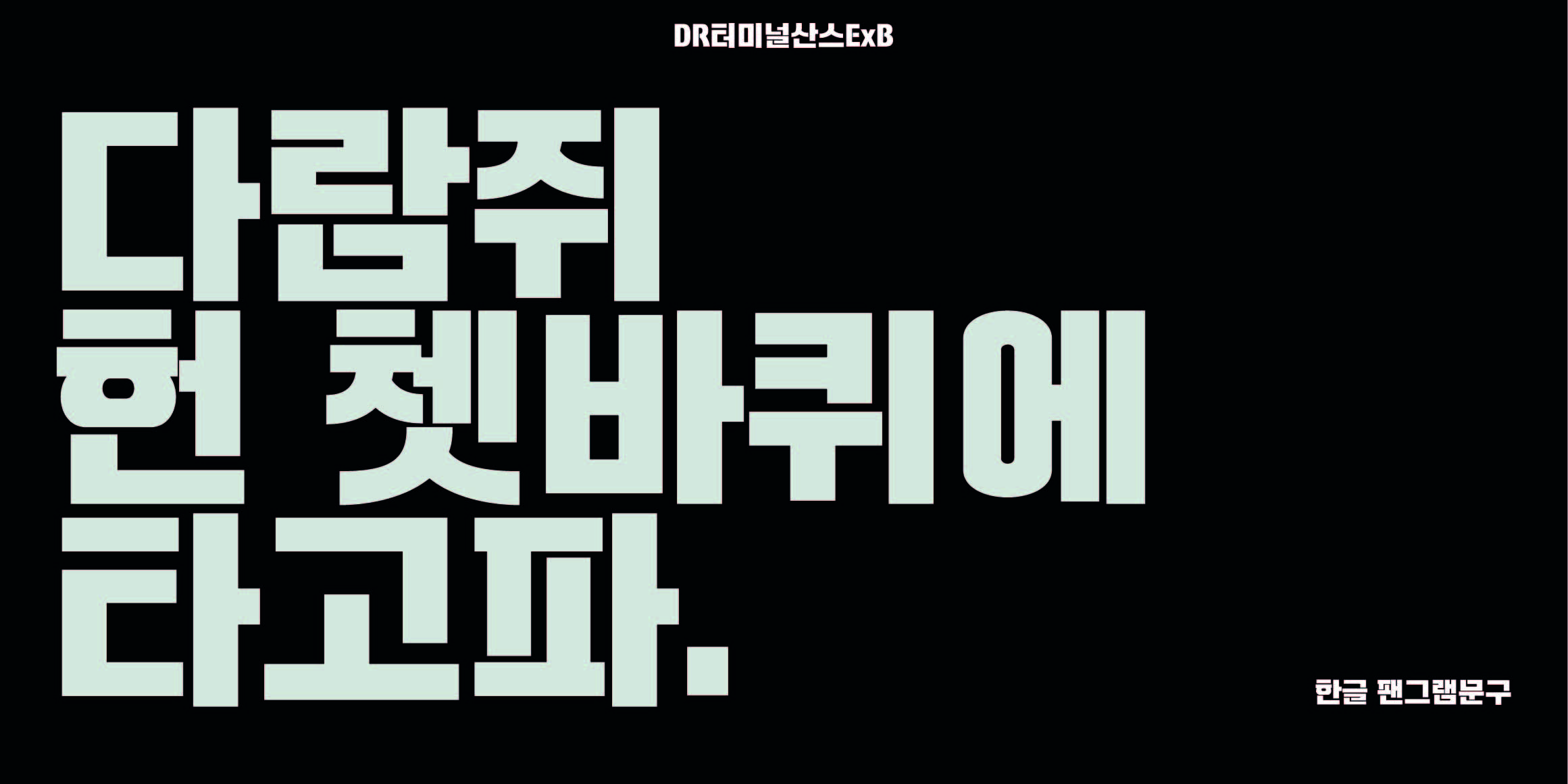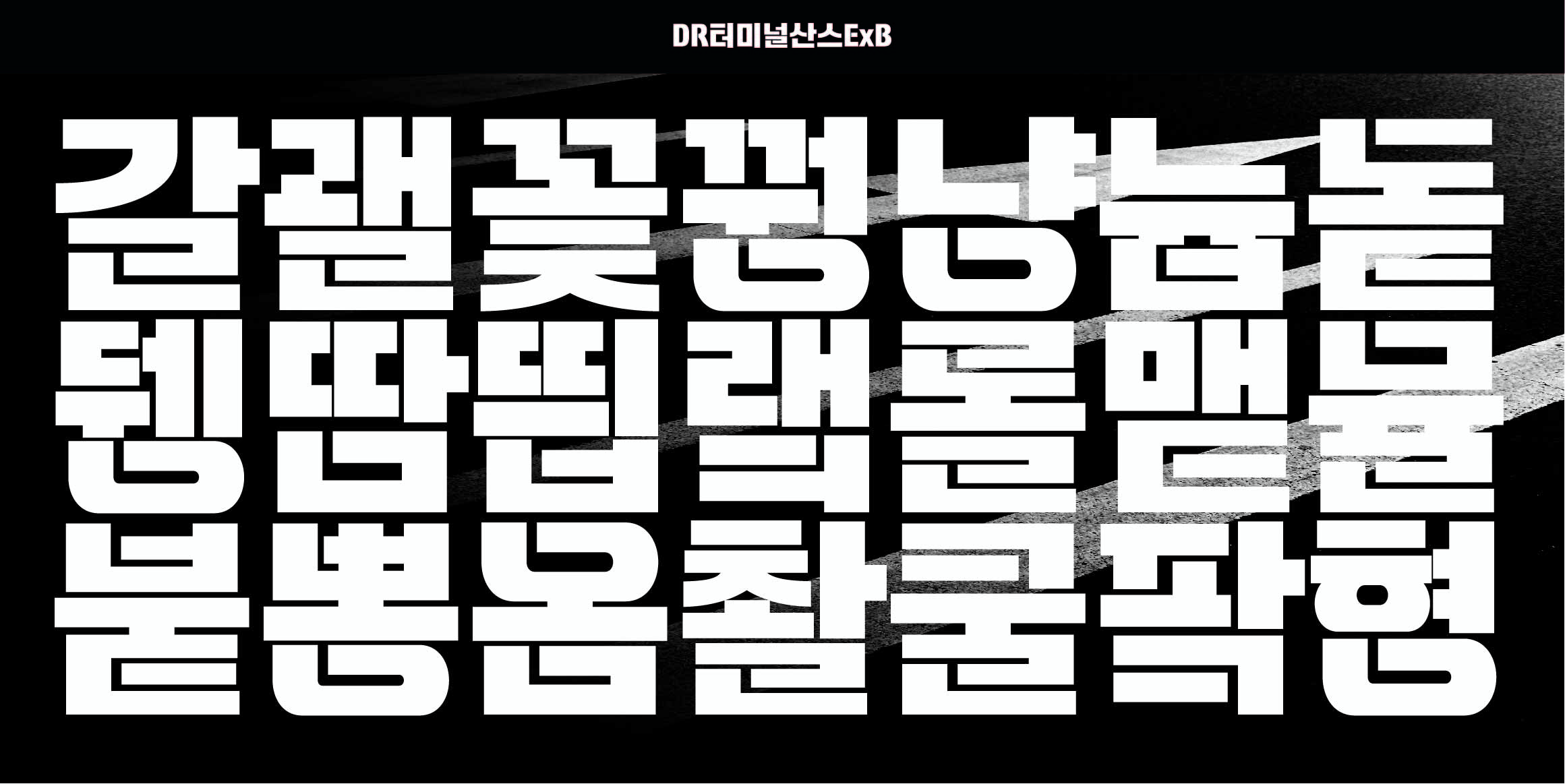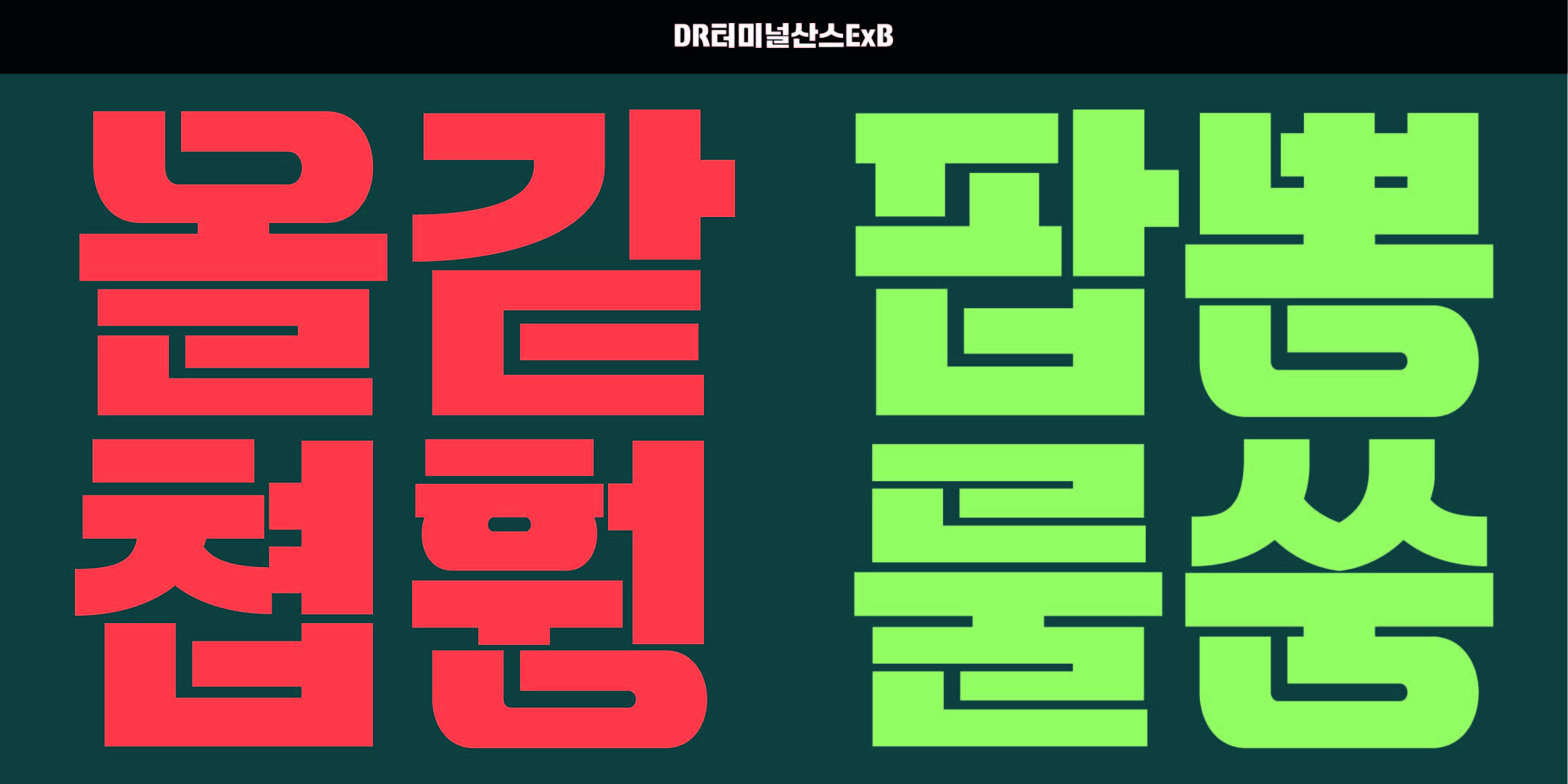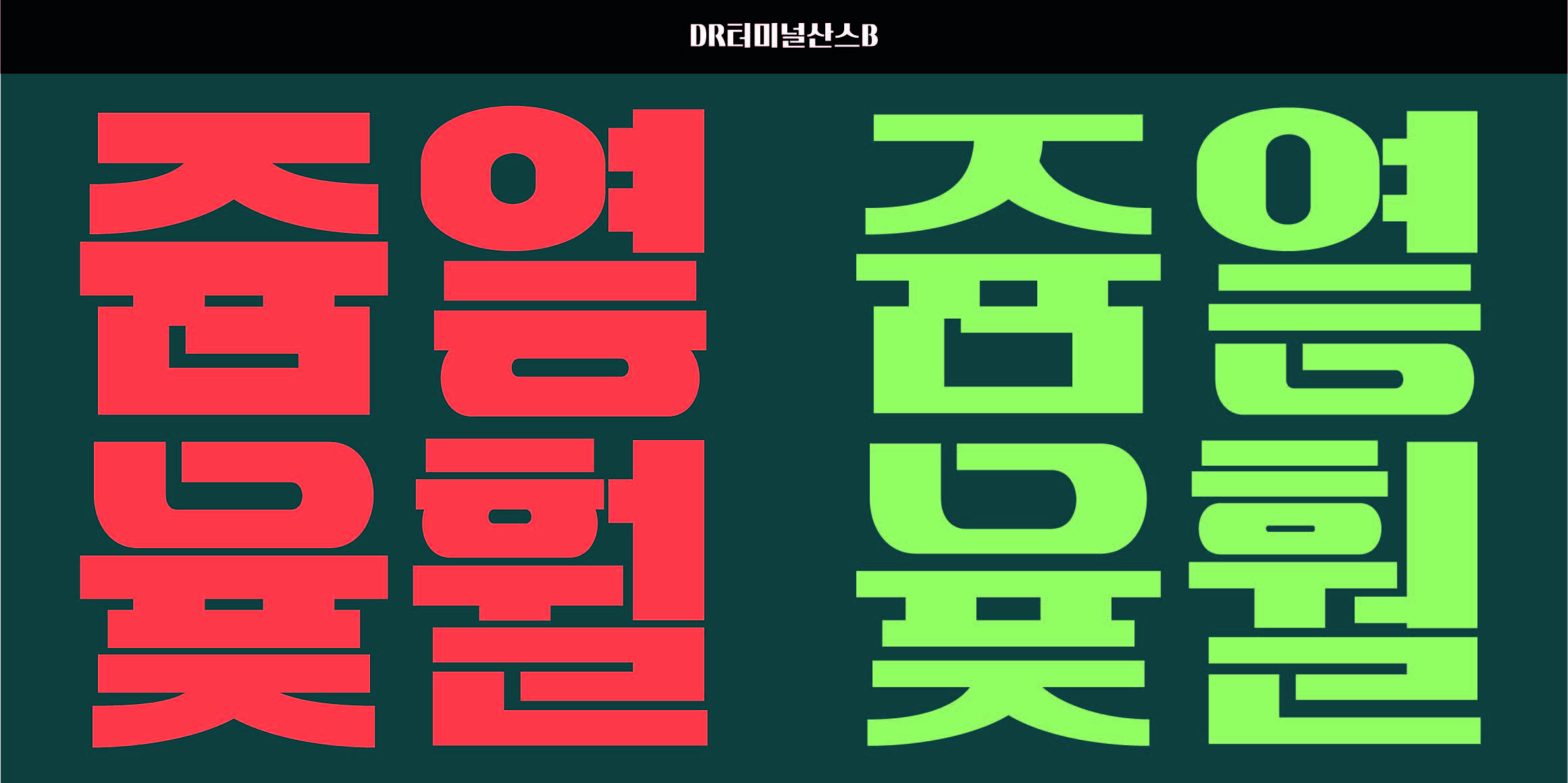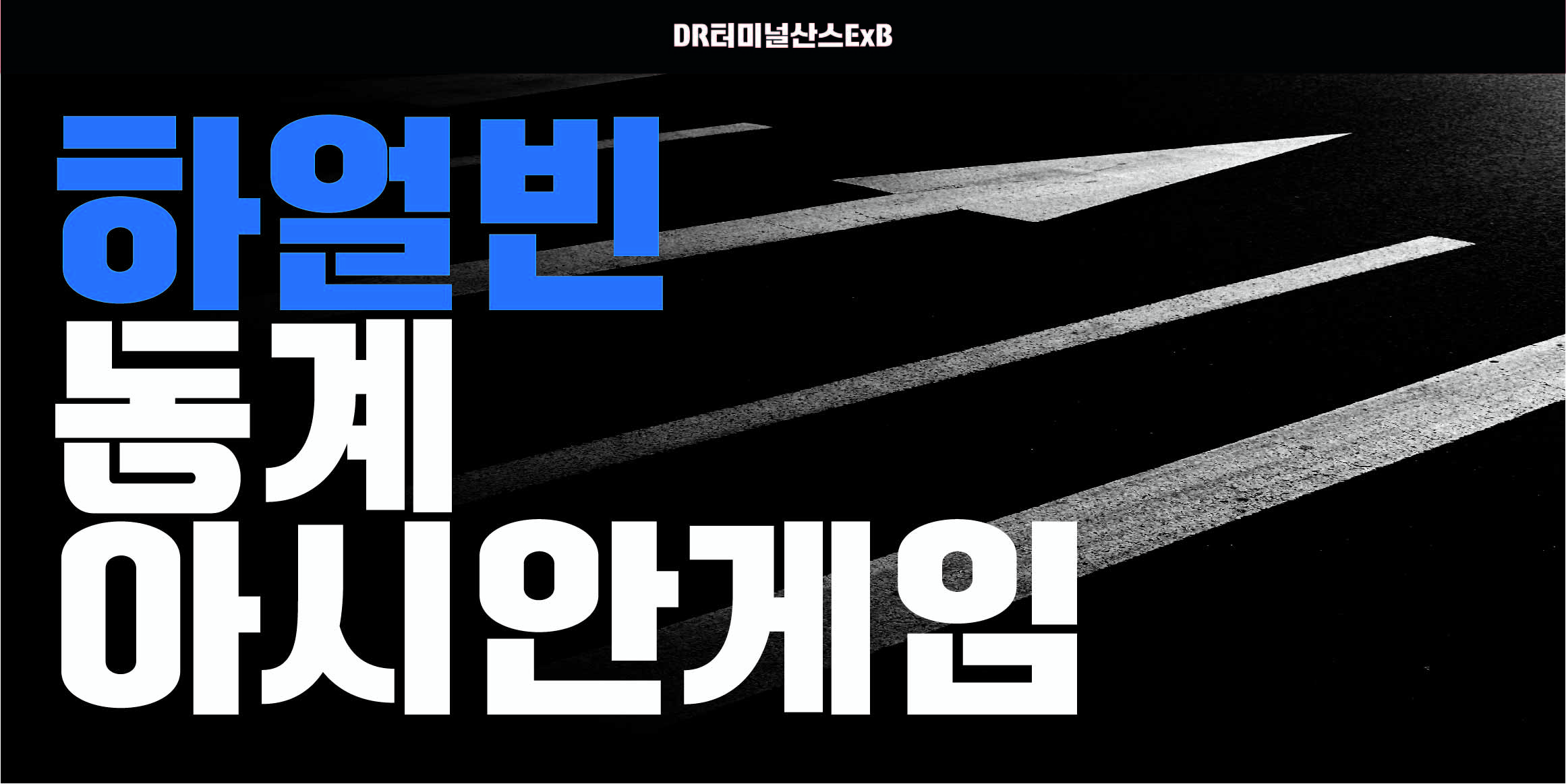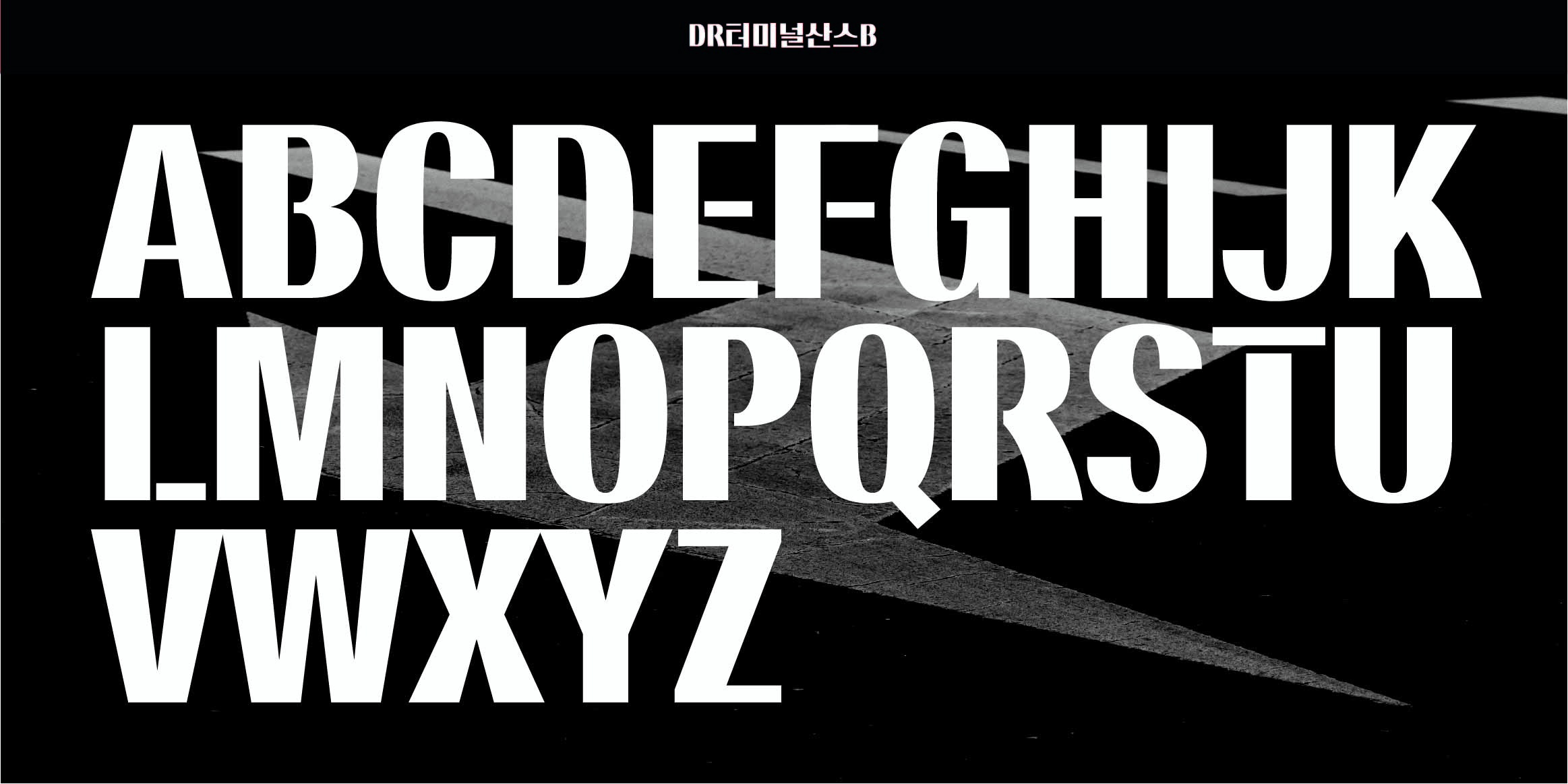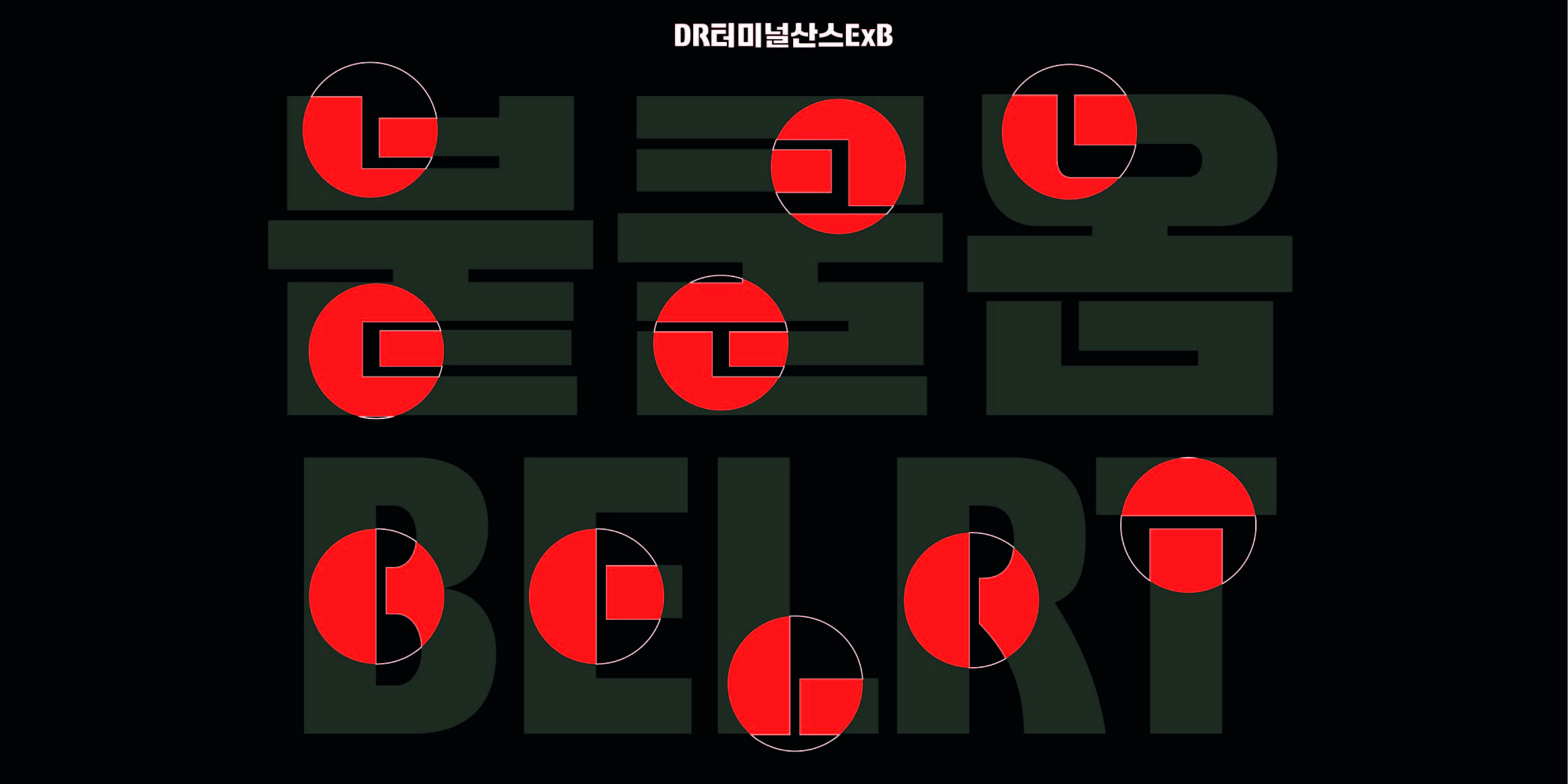
DR터미널산스
Doctorfont
부드러운 표정을 가진 터미널(Terminal)체를 현대적인 감각으로 재해석한 터미널산스(Terminal Sans)는 스텐실(Stencil) 효과가 더욱 돋보이는 디자인이 특징이며, ExtraBold와 Bold 두 가지 굵기로 구성되어 있어 강한 주목성을 요구하는 헤드라인용 서체로서 활용도가 높으며, 다양한 디자인 프로젝트에서 개성 있고 인상적인 타이포그래피를 연출하는 데 적합합니다.